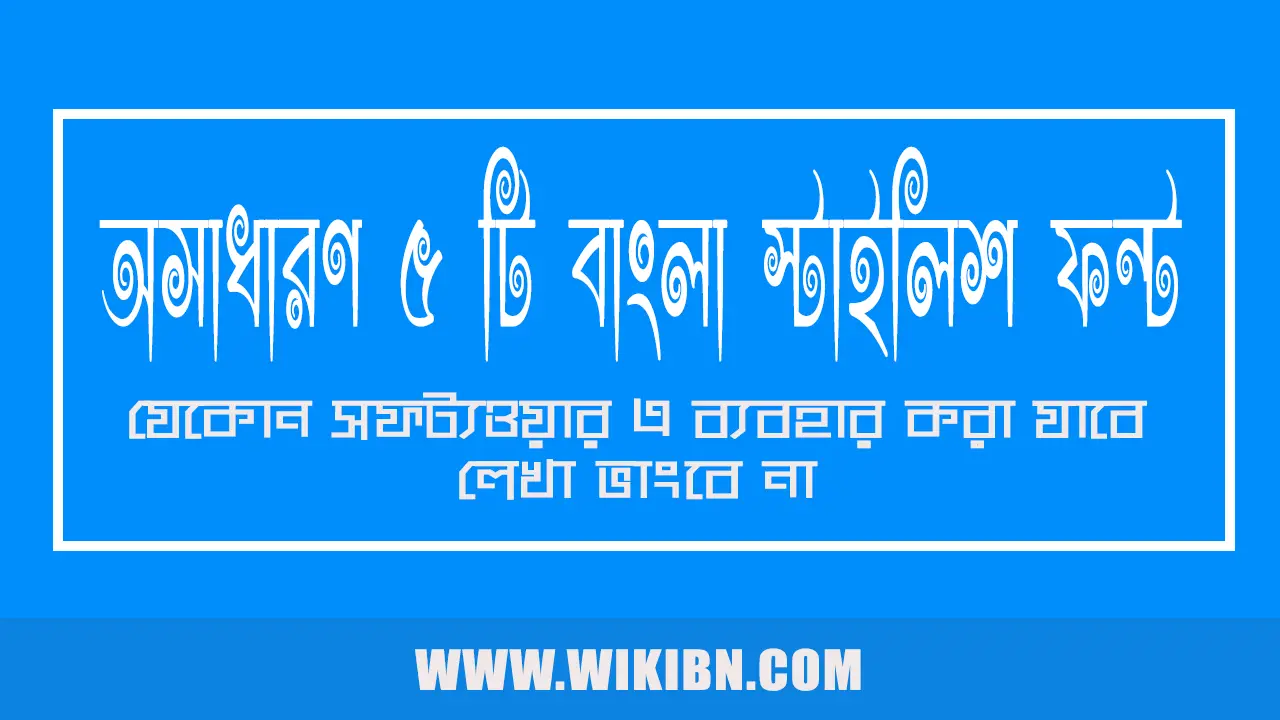
Awesome 5 Bangla Stylish Fonts | অসাধারণ ৫ টি বাংলা স্টাইলিশ ফন্ট ফ্রিতে ডাউনলোড করে নিন
বাংলা লেখাকে স্টাইলিশ করার জন্য কিংবা বাংলাতে লোগো বা ব্যানার তৈরীর জন্য বাংলা স্টাইলিশ ফন্ট (Bangla Stylish Fonts) এর প্রয়োজন পড়ে। ডেস্কটপ কিংবা মোবাইল ফোনে খুব বাংলা স্টাইলিশ ফন্ট গুলোন ইন্সটাল থাকে না। তাই আমাদেরকে আমাদের প্রয়োজনে স্টাইলিশ ফন্টগুলোন খুঁজে বের করে ইন্সটাল করে নিতে হয়। আর, আজকের এই টিউনে আমি আপনাদের নিকট শেয়ার করব জনপ্রিয় ৫ টি বাংলা স্টাইলিশ ফন্ট যেগুলো ব্যবহার করে আপনি আপনার বাংলা লেখা আর্কষণীয় করে তুলতে পারবেন।
Bangla Stylish Font কী?
মূলত বাংলা লেখাকে আকর্ষনীয় করার জন্য Bangla Stylish Font ব্যবহার করা হয়। কোন ডকুমেন্ট তৈরী করার সময় কিংবা কিছু লেখাকে অন্য সব লেখা থেকে আলাদা দেখানোর প্রয়োজন পড়ে। এছাড়াও লোগো ডিজাইন কিংবা ব্যানার তৈরিতে বাংলা স্টাইলিশ ফন্ট এর ব্যবহার উল্লেখযোগ্য। এসব এর পাশাপাশি বর্তমানে ওয়েবসাইটের বাংলা লেখাকে আকর্ষনীয় করার জন্য বাংলা স্টালিশ ফন্ট ব্যবহার করা হয়ে থাকে।
Bangla Stylish Font এর নাম
এই টিউনে যে ৫ টি স্টাইলিশ ফন্ট শেয়ার করব সেই ৫ টি ফন্টের নাম –
- Rajon Shoily
- SomeshwarEMJ
- MonooMJ
- Modhumati
- ChitraMJ
Awesome 5 Stylish Bangla Fonts Demo and Details
৫ টি বাংলা স্টাইলিশ ফন্ট ডেমো, ডিটেইলস সহ দিয়ে দিলাম। ভালো লাগলে ডাউনলোড করে নিন।
Rajon Shoily
Font Name: Rajon Shoily
SomeshwarEMJ
Font Name: SomeshwarEMJ
MonooMJ
Font Name: MonooMJ
Modhumati
Font Name: Modhumati
ChitraMJ
Font Name: ChitraMJ